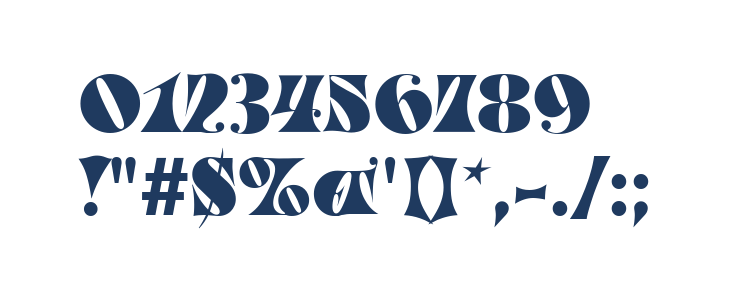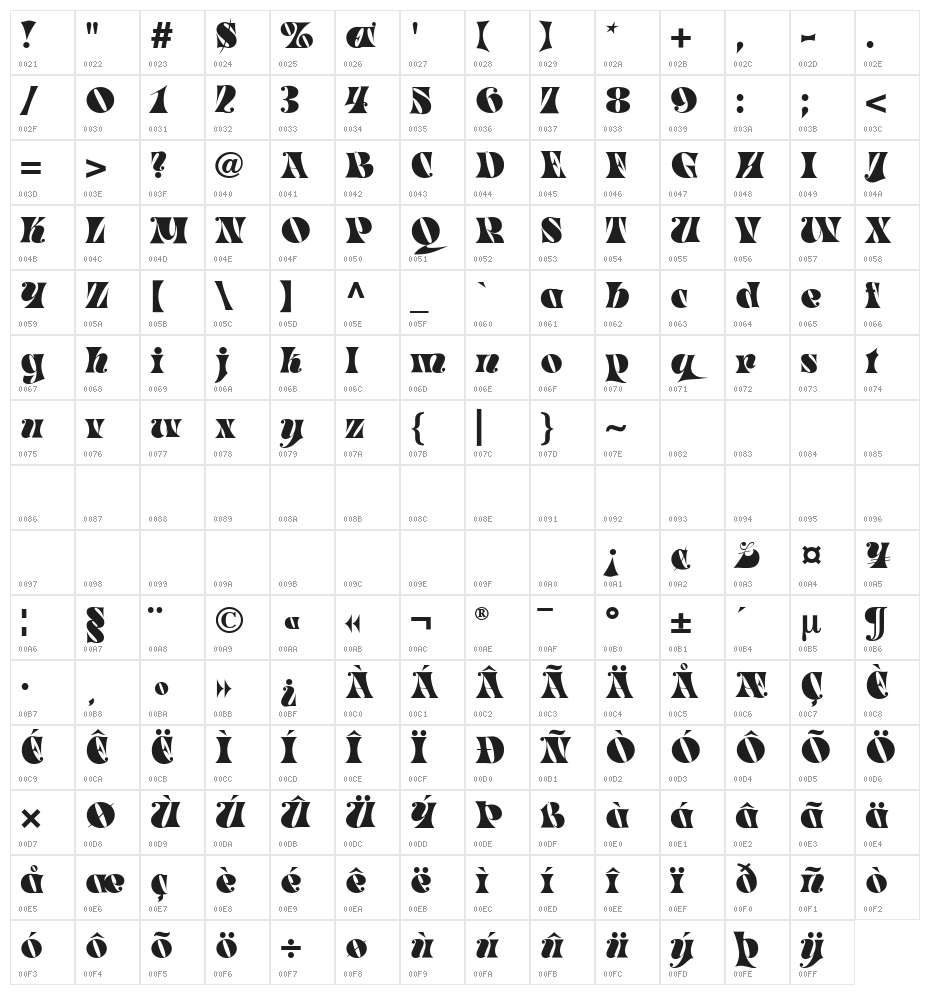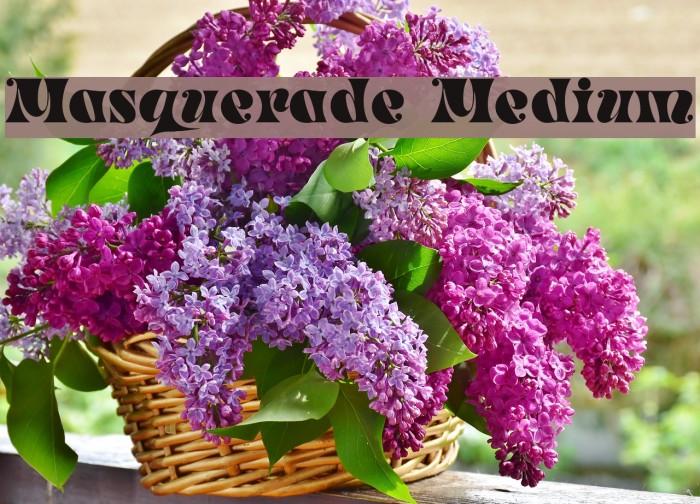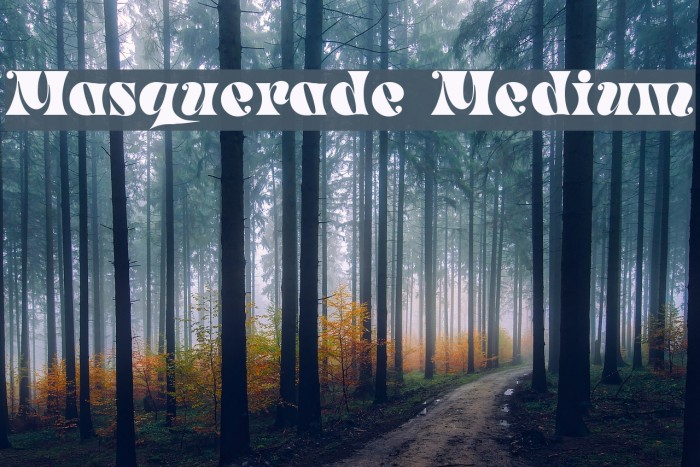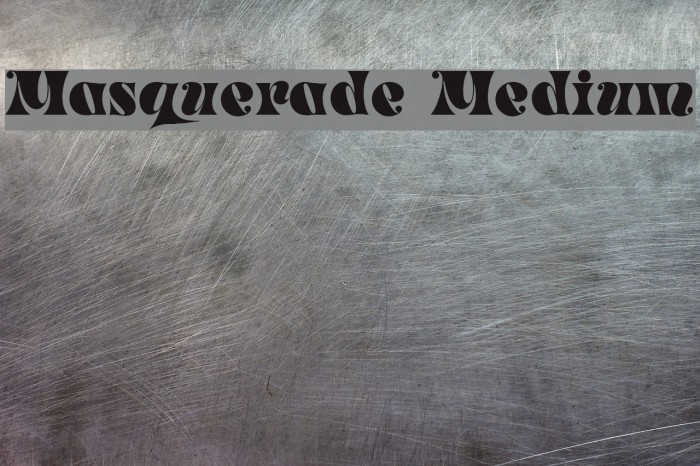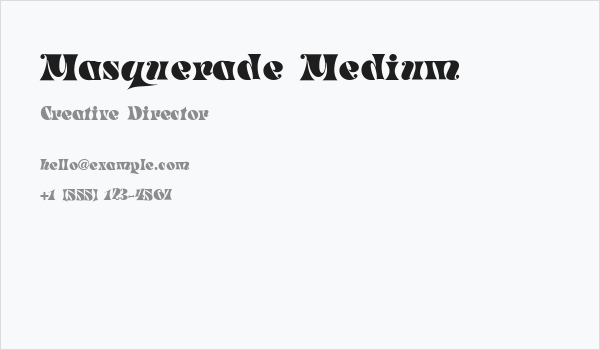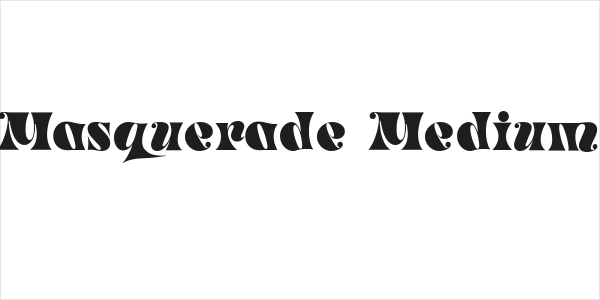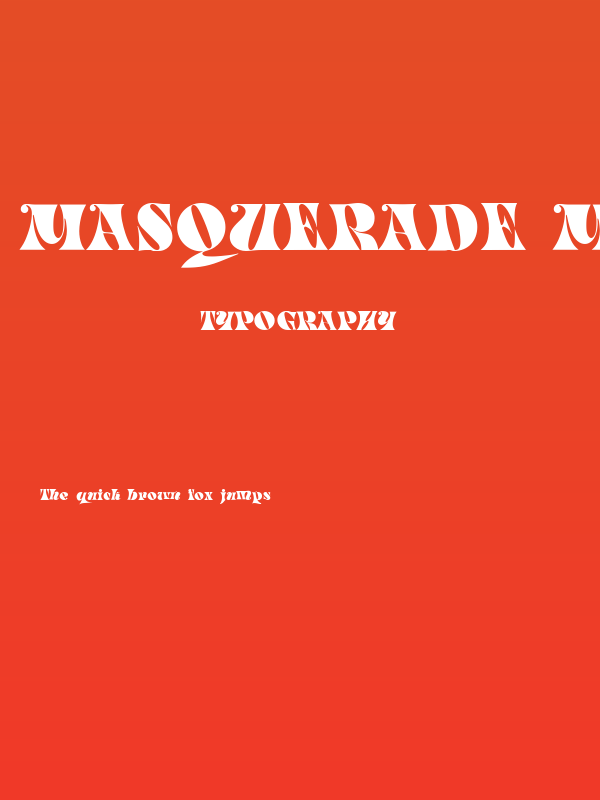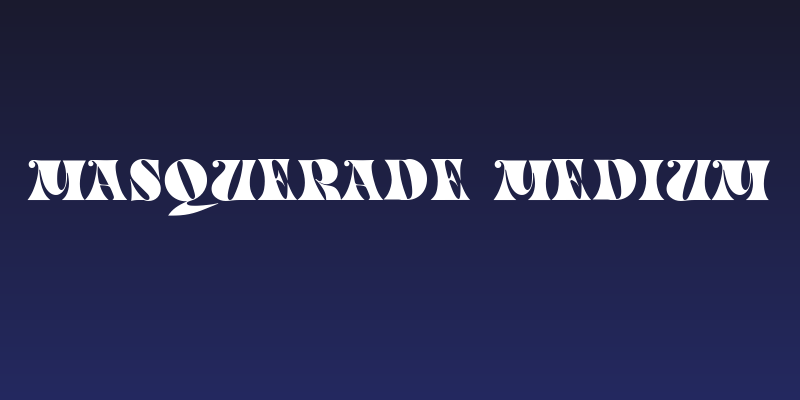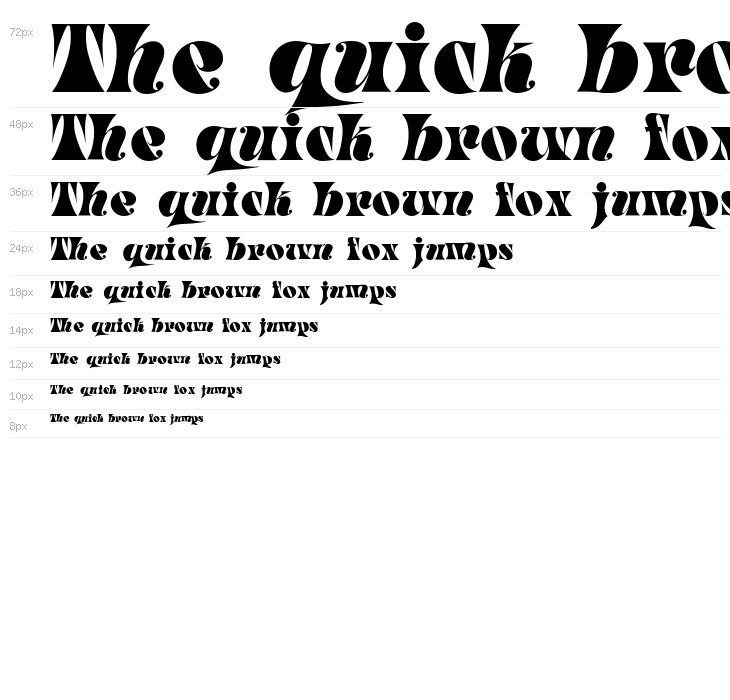
Masquerade Medium Font
| Gesamtstil | Vintage, Decorative |
| Vorgeschlagene Projekte | Ideal for posters, event invitations, branding for creative industries, and any project requiring a bold, artistic touch. |
Masquerade Medium